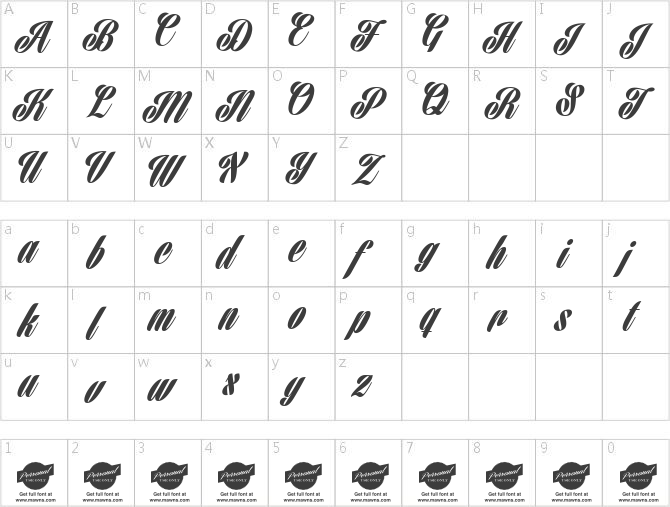
字體名稱: Harbell
Harbell Personal Use Only
Harbell Personal Use Only介紹
Harbell Personal Use Only字體字庫是一款讓人賞心悅目、百看不厭的英文字體,適合各類廣告和產品包裝設計應用,字體大小0.17MB,格式為ttf字體,上傳用戶是M_墨董,作者/版權方為未知